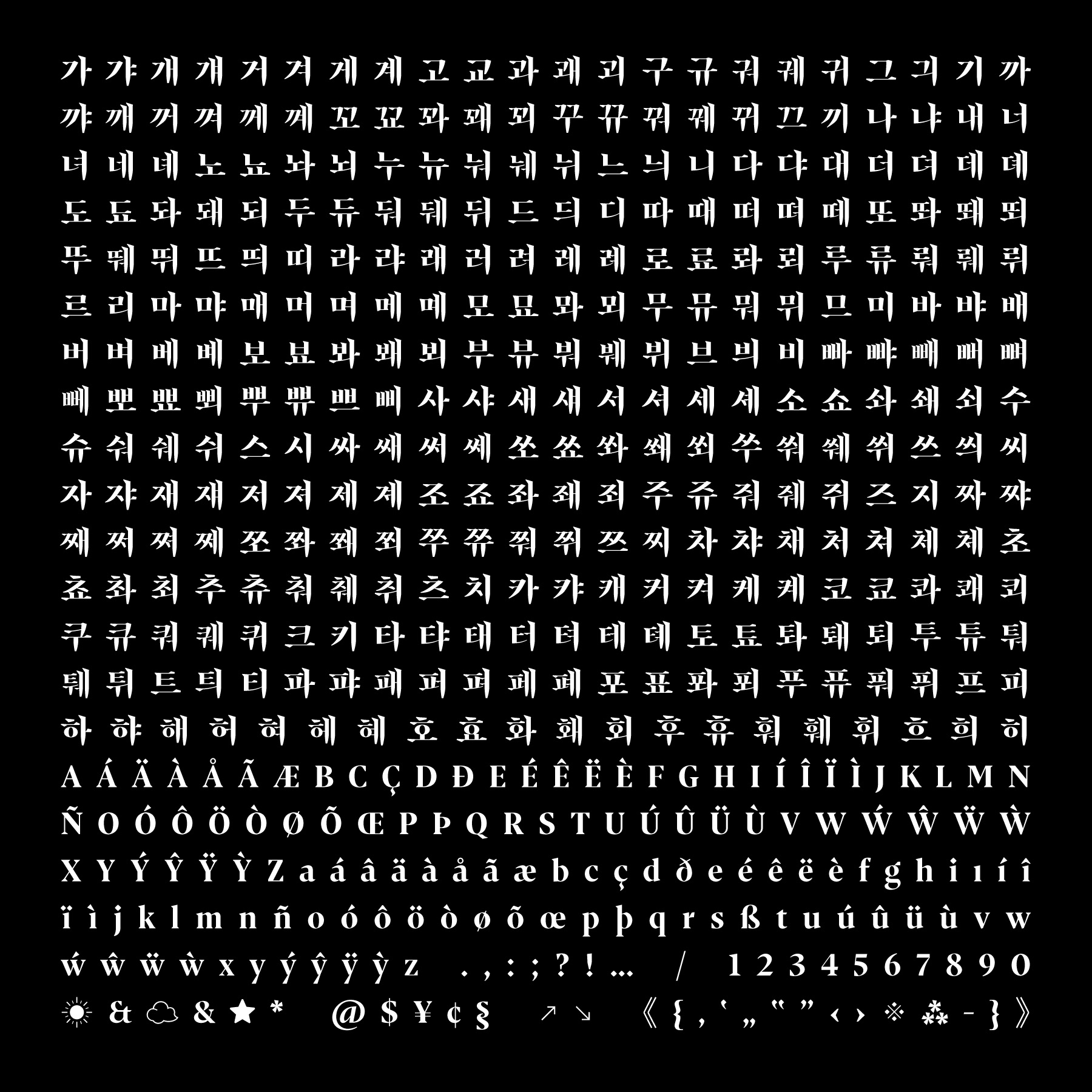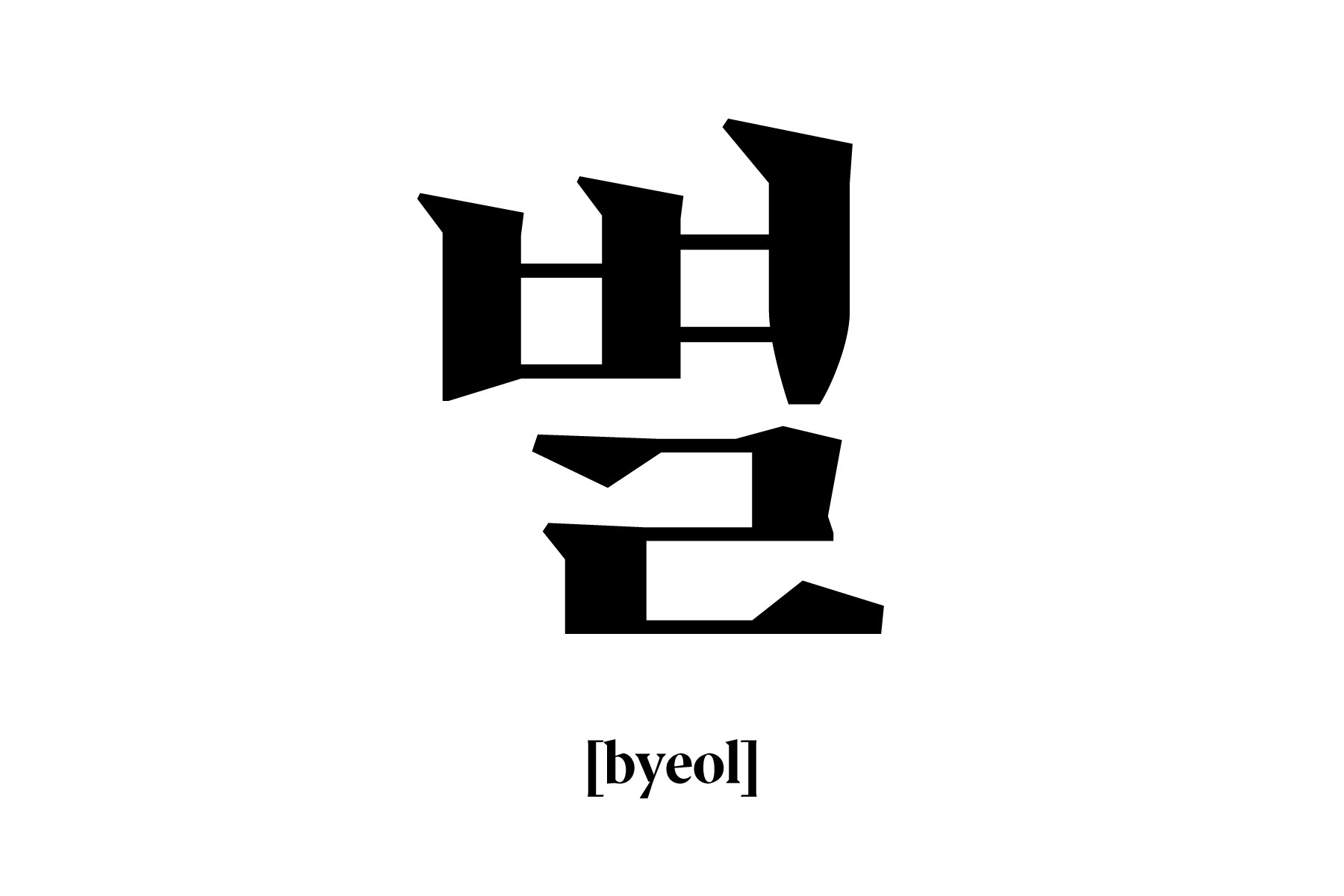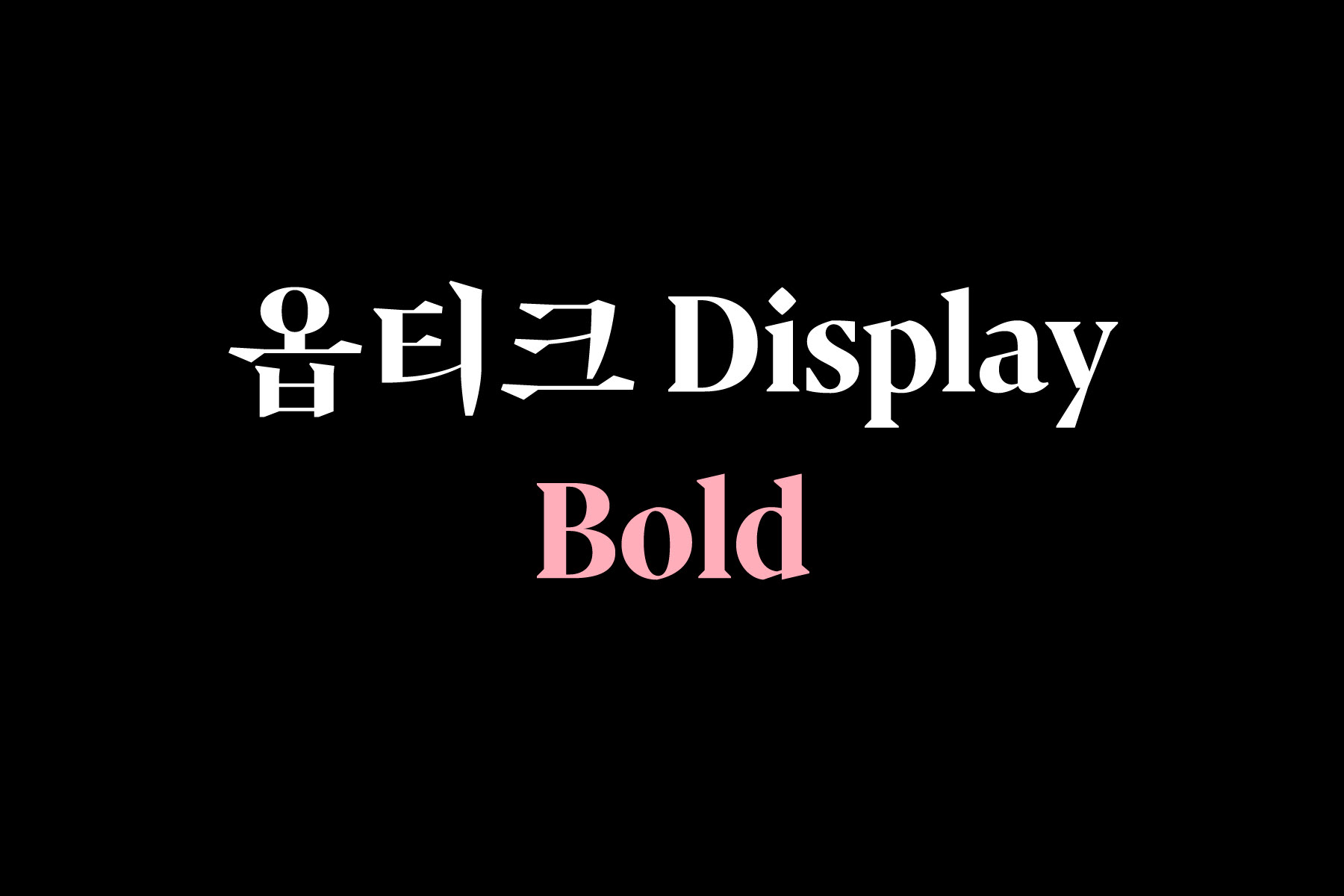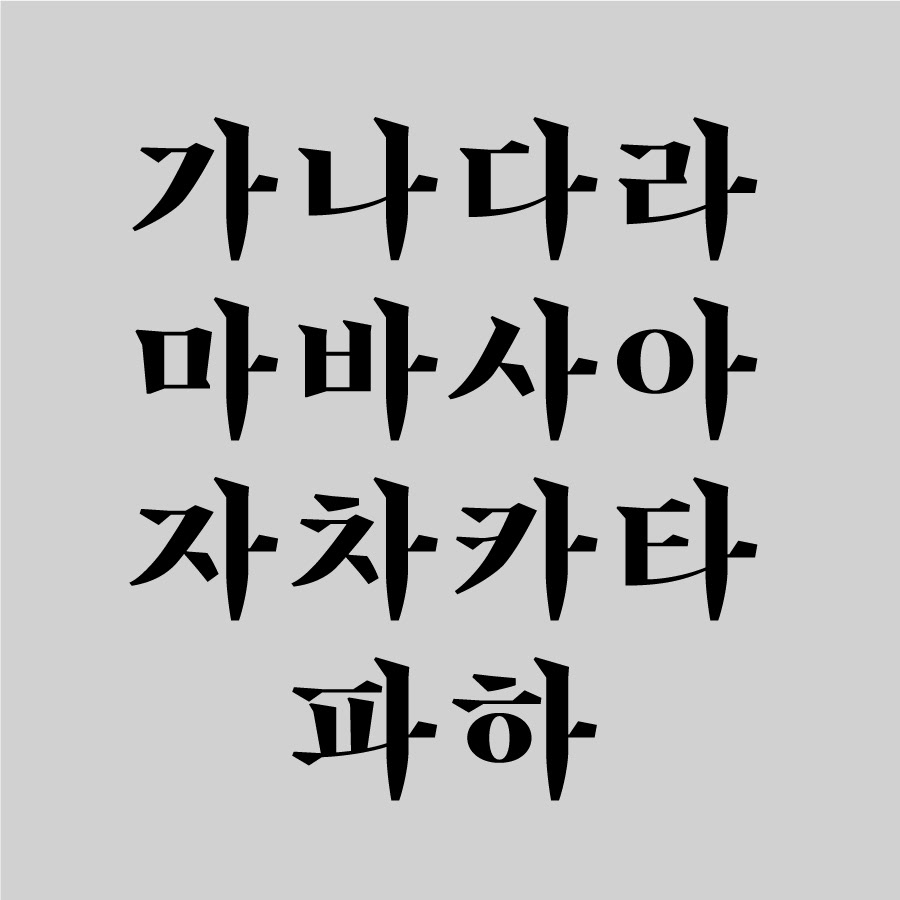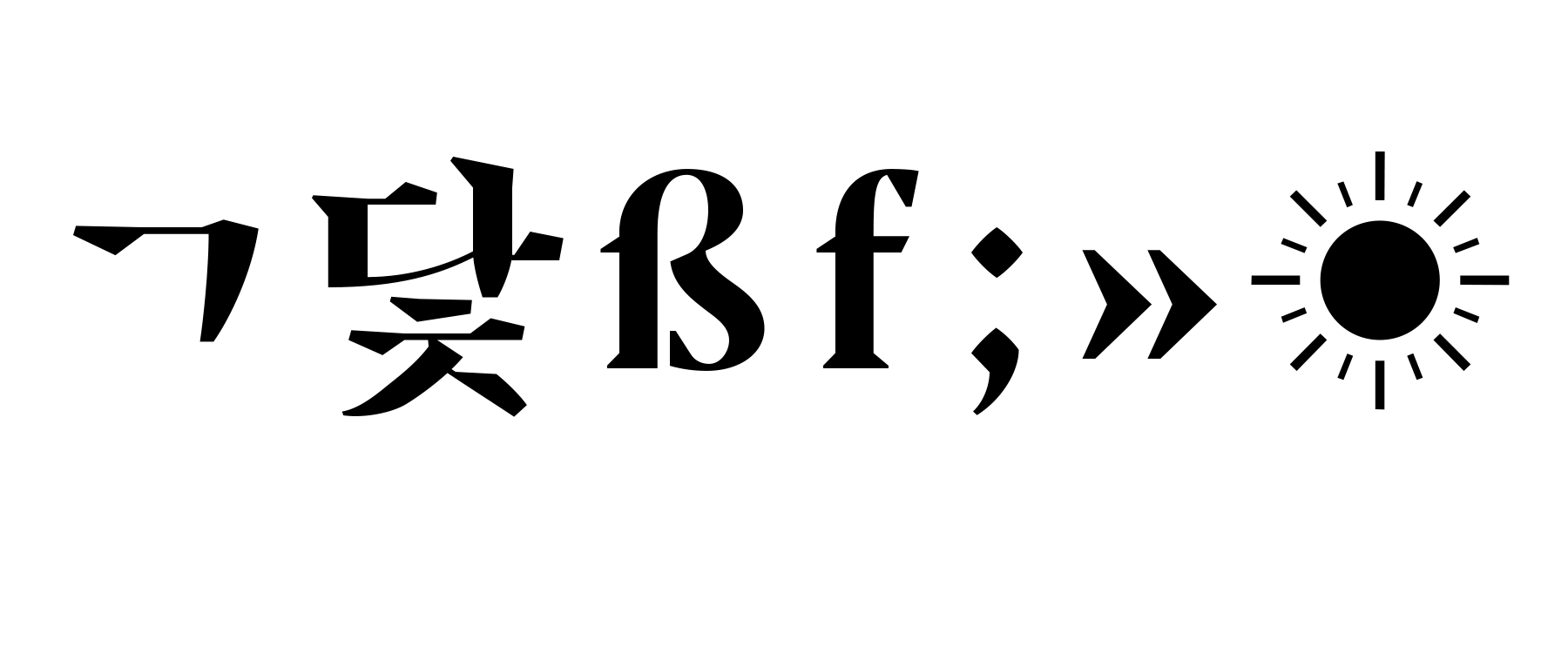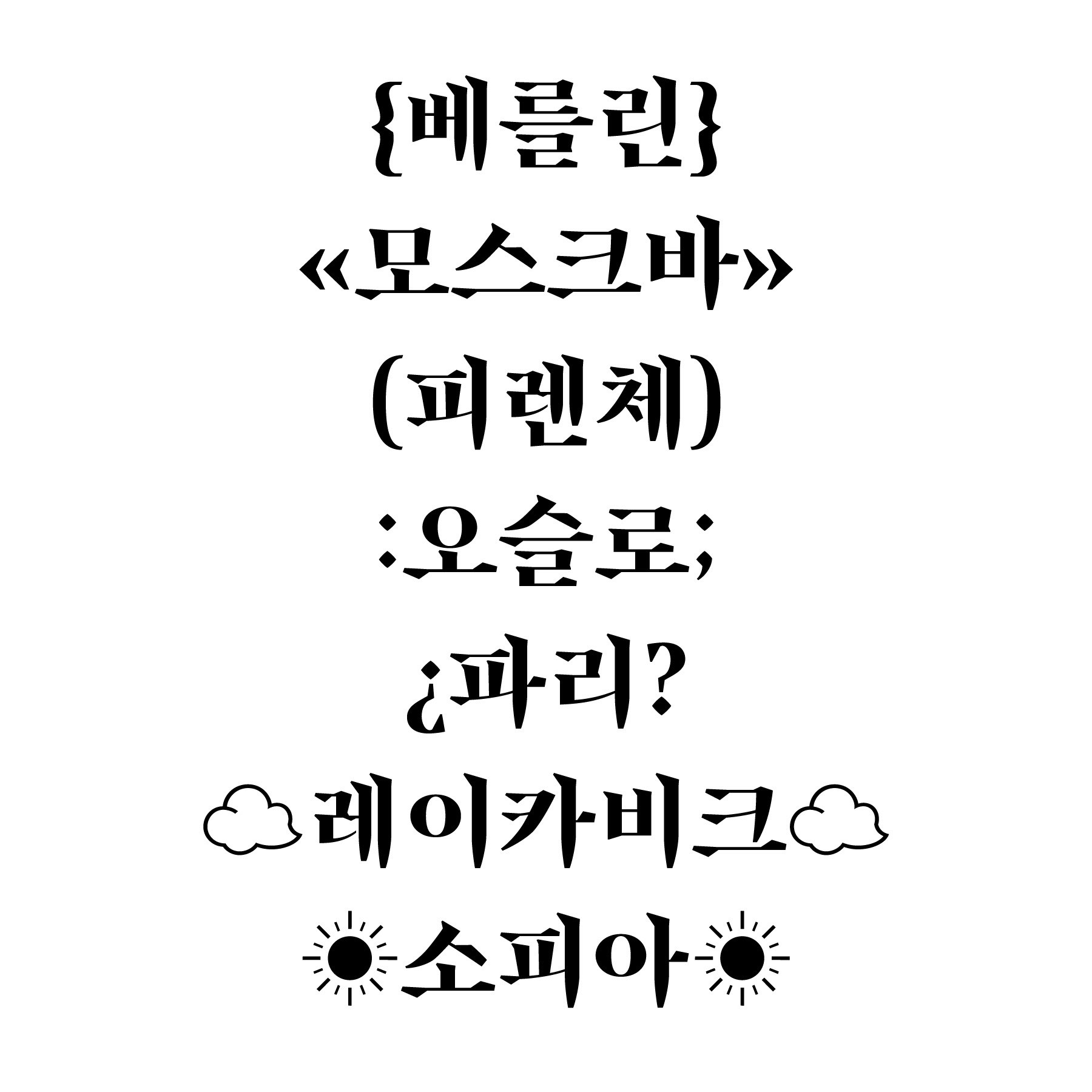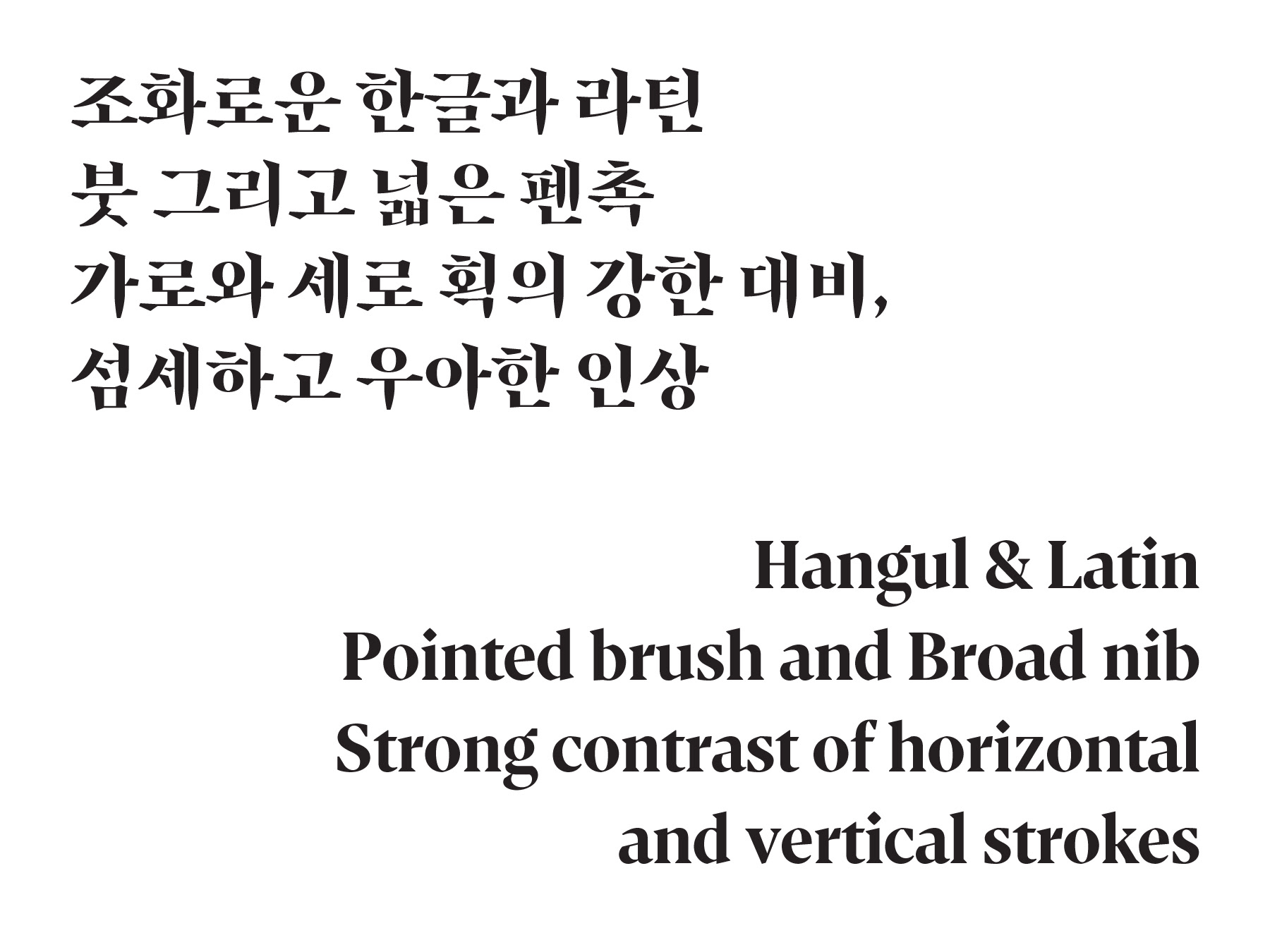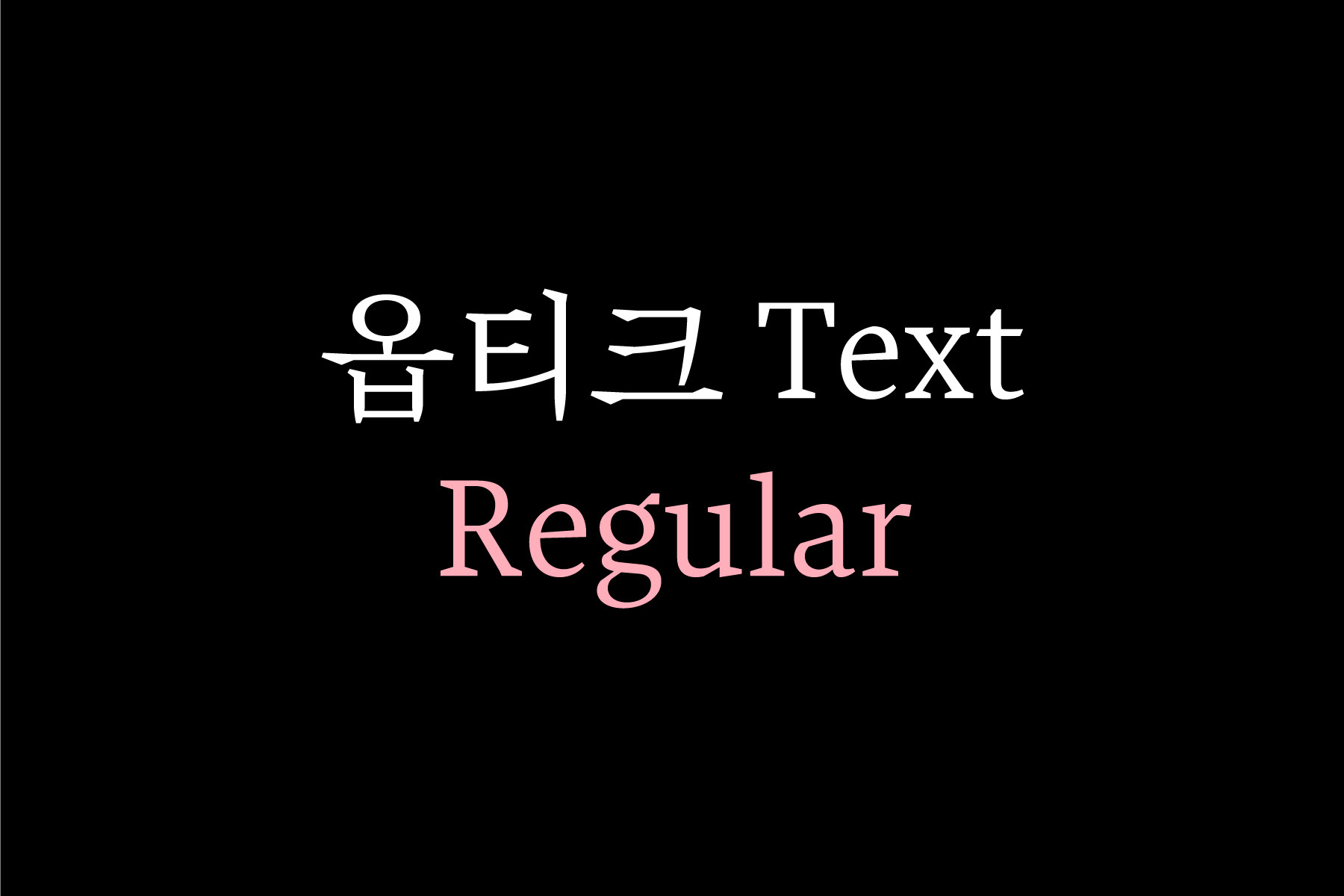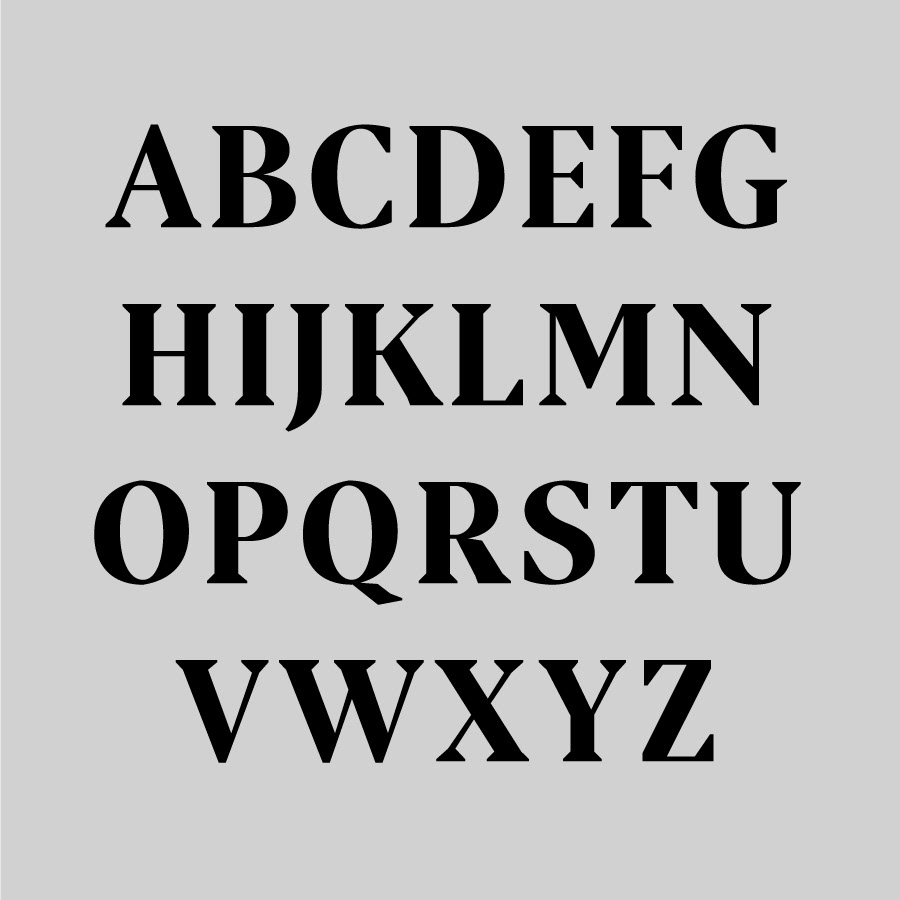
옵티크
Optique
한글과 라틴을 위한 다국어 글꼴 디자인 프로젝트
Multilingual typeface design project for Latin and Hangul in optical sizes
«옵티크»는 한글과 라틴 문자를 위한 다국어 글꼴 디자인 프로젝트이다. 각 문자 고유의 쓰기 도구, 즉 한글은 붓, 라틴 문자는 넓은 펜촉을 바탕으로 디자인하여 서로 다른 두 문자의 인상을 조화롭게 만들었다. 옵티크는 시각적 크기에 따라 글자가족을 본문용과 제목용으로 나누어 구성했다는 의미로 프랑스어 옵티크(Optique)에서 따 왔다.
«옵티크 텍스트»는 낮은 굵기 대비와 큰 속공간으로 작은 크기에서 잘 읽히는 본문용 글꼴로 디자인했고, «옵티크 디스플레이»는 높은 굵기 대비와 돋보이는 세리프로 독자의 눈길을 끌 수 있는 제목용 글꼴로 디자인했다.
2019년 디스플레이 Regular, Bold 버전을 출시했으며, 텍스트 버전을 출시 예정이다.
* 이 글꼴은 노은유의 헤이그왕립예술학교 타입미디어 졸업 작품이다. (http://typemedia2017.com/eunyou)
* Typographica의 ‘Our Favorite Typefaces of 2019’로 선정되었다. (https://typographica.org/typeface-reviews/optique-display)
«Optique» is a serif typeface based on the tools of each script; broad nib for Latin and pointed brush for Hangul. «Optique» simplifies the shapes of Latin and Hangul while preserving the way of writing for each script. It is designed to achieve unity; to have the two scripts appear as one. It consists of three styles: text regular, display regular, and bold.
«Optique Text» has lower contrast and a larger x-height than the display version.
«Optique Display» is intended to stand out and create a mood that entices the reader into the text. It has high contrast with more pronounced serifs.
«Optique Display» regular and bold was released in 2019 with «Optique Text» scheduled to be released in 2021.
* This typeface was Eunyou Noh’s graduate project at the Royal Academy of Arts, The Hague (KABK).
* Chosen as ‘Our Favorite Typefaces of 2019’ by Typographica.
- 오픈타입 정보: 커닝, 언어별 문장부호, 멀티 글리프
- OpenType feature : Kerning, Local Punctuation, Multi-glyphs